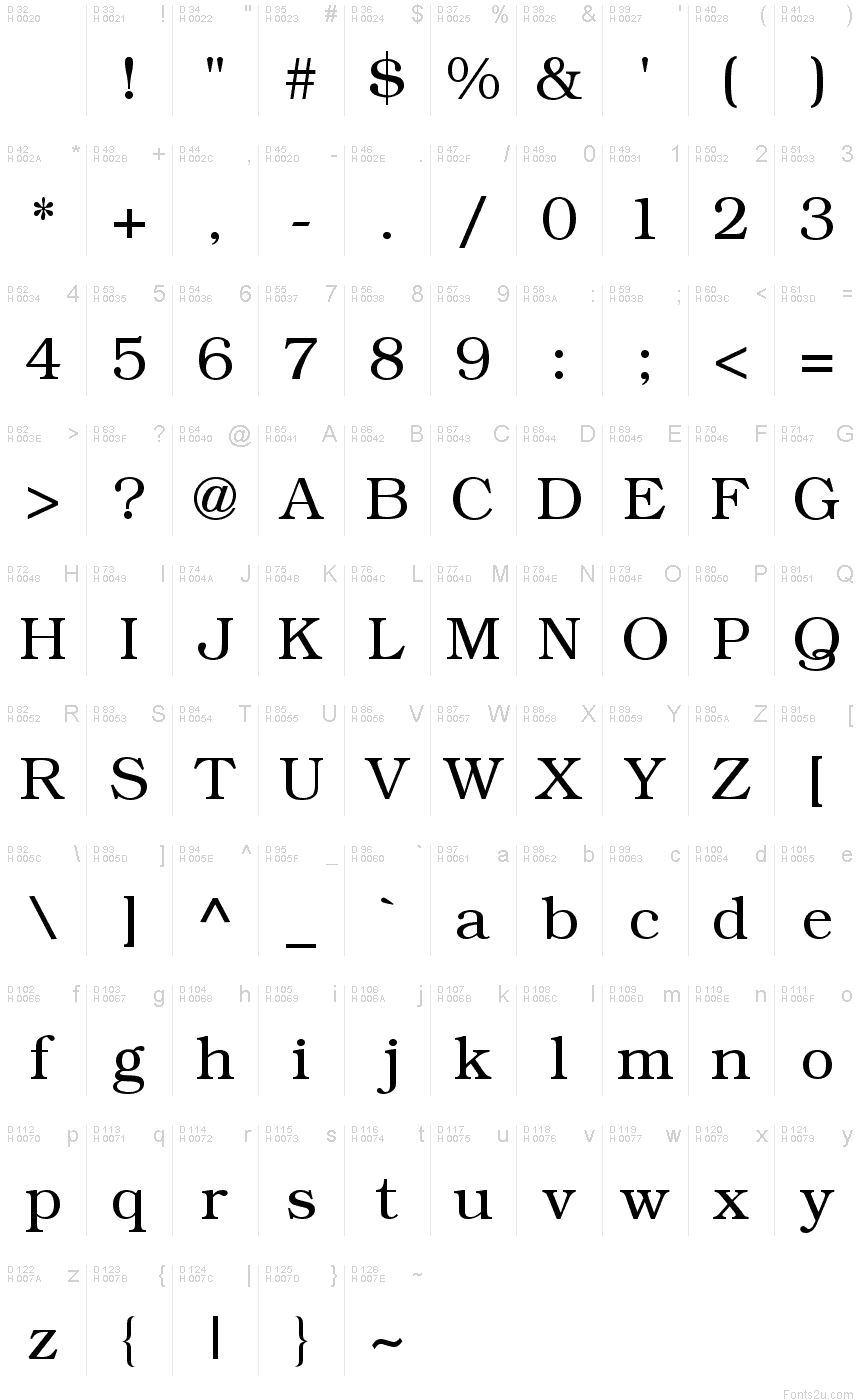
ER Bukinist Mac
يعد خط ER Bukinist Mac، الذي صممه Gavin Helf، خطاً مجانياً ذا طابع أدبي بزوائد (serif)، يتمتع بالوقار الهادئ لصفحة عنوان كتاب كثرت قراءته. تضفي أشكاله العريضة والمهيبة وزوائده الواضحة والبسيطة وزناً أدبياً على الكلمات دون أن تبدو جامدة، مما يجعله خطاً أنيقاً وسهل القراءة ويحمل لمسة من الحنين إلى الماضي.
يعمل خط ER Bukinist Mac بشكل رائع في تصميم أغلفة الكتب، وهويات المكتبات، والعناوين التحريرية، وقوائم المقاهي، وبطاقات الدعوة، ومواد المتاحف، وتغليف المنتجات الفاخرة. اضبط الخط بحجم أكبر قليلاً ليأخذ إيقاعه السخي مساحته، وقم بإقران هذا الخط المجاني مع خط (sans) هادئ مثل Helvetica للحصول على تباين نظيف وعصري.